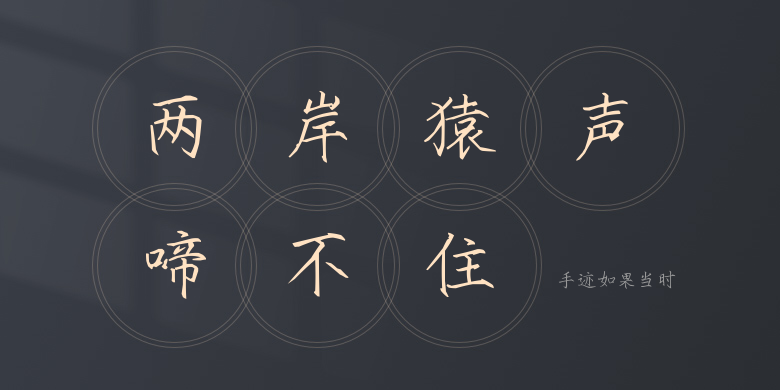
手迹如果当时
手迹如果当时,这款字体结构工整、笔画清晰,兼顾美观与易读性,适用于标题、正文、海报、包装、LOGO 等多种场景。字形优雅稳定,风格百搭耐看,适配日常排版与创意设计,让文字呈现更舒适、更具质感。手迹如果当时一笔一画,皆是细节,以均衡的比例、流畅的线条打造舒适视觉体验,字形端正大气,风格简约现代。无论是商业设计、品牌宣传还是日常排版,都能轻松驾驭,让文字更有格调与力量。手迹如果当时字体下载。